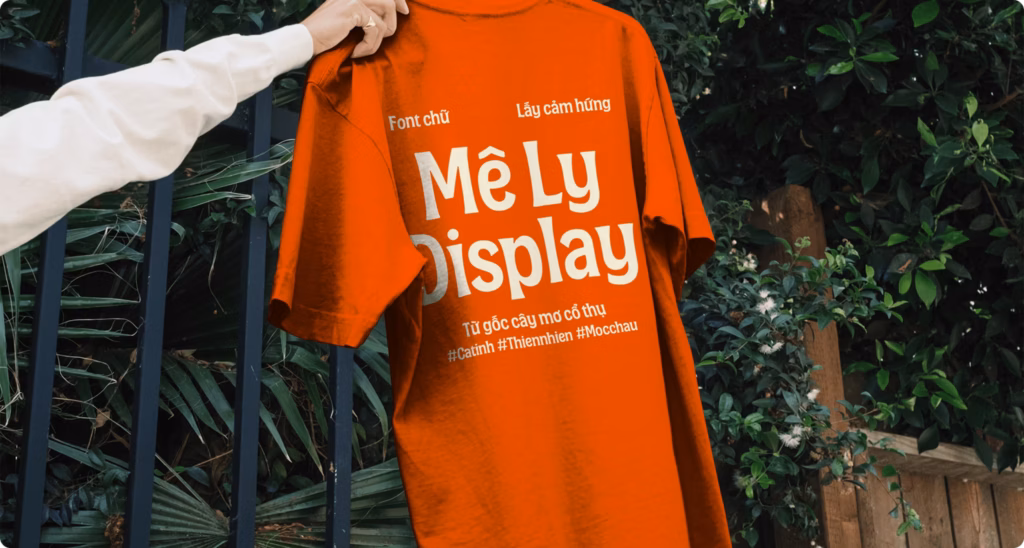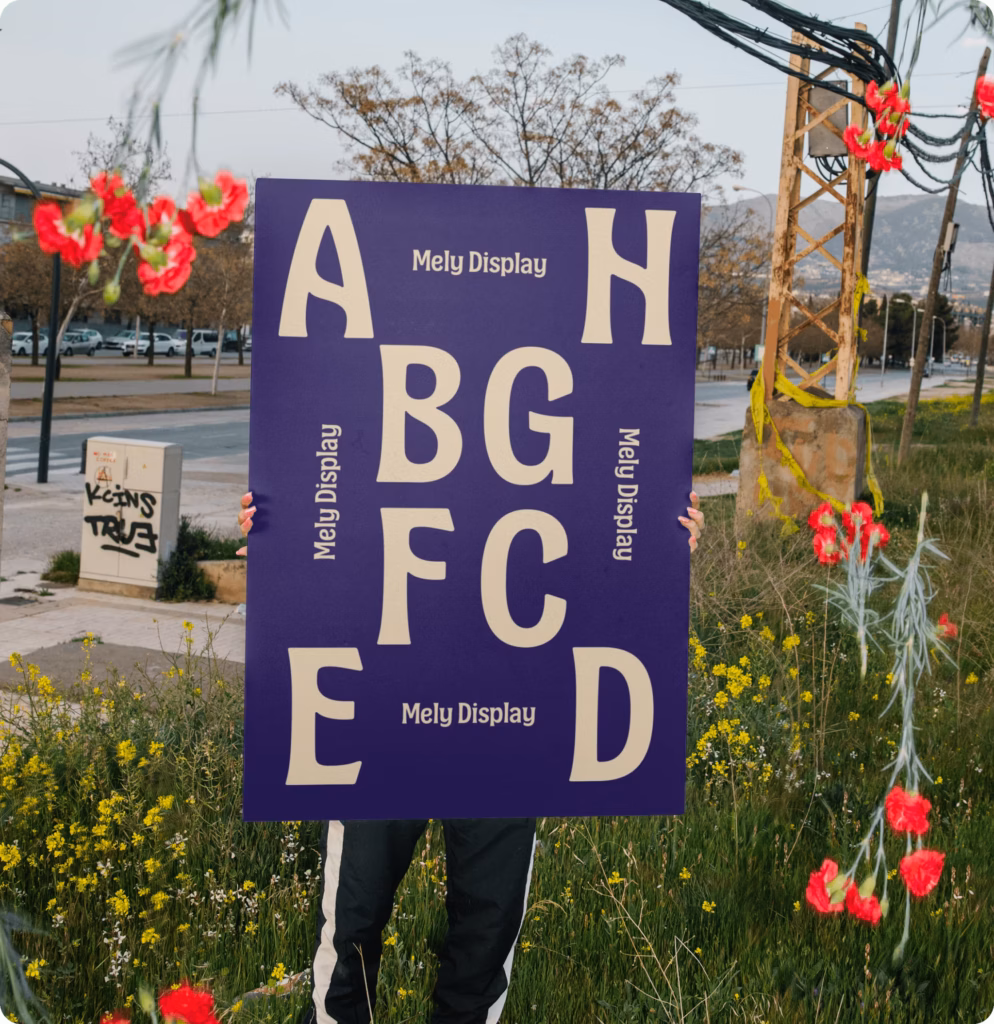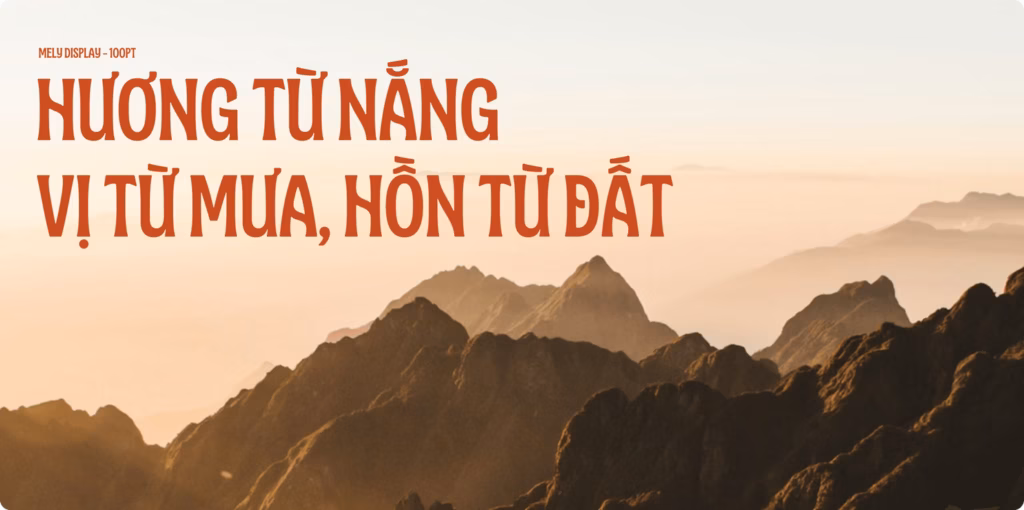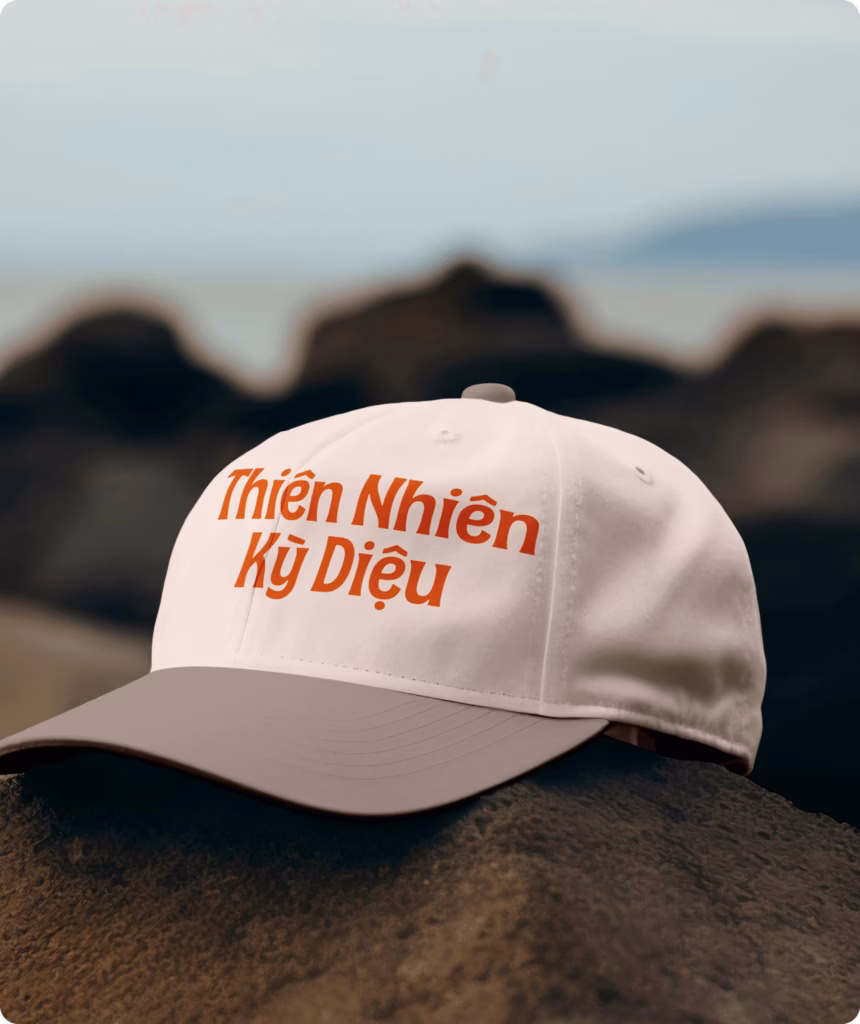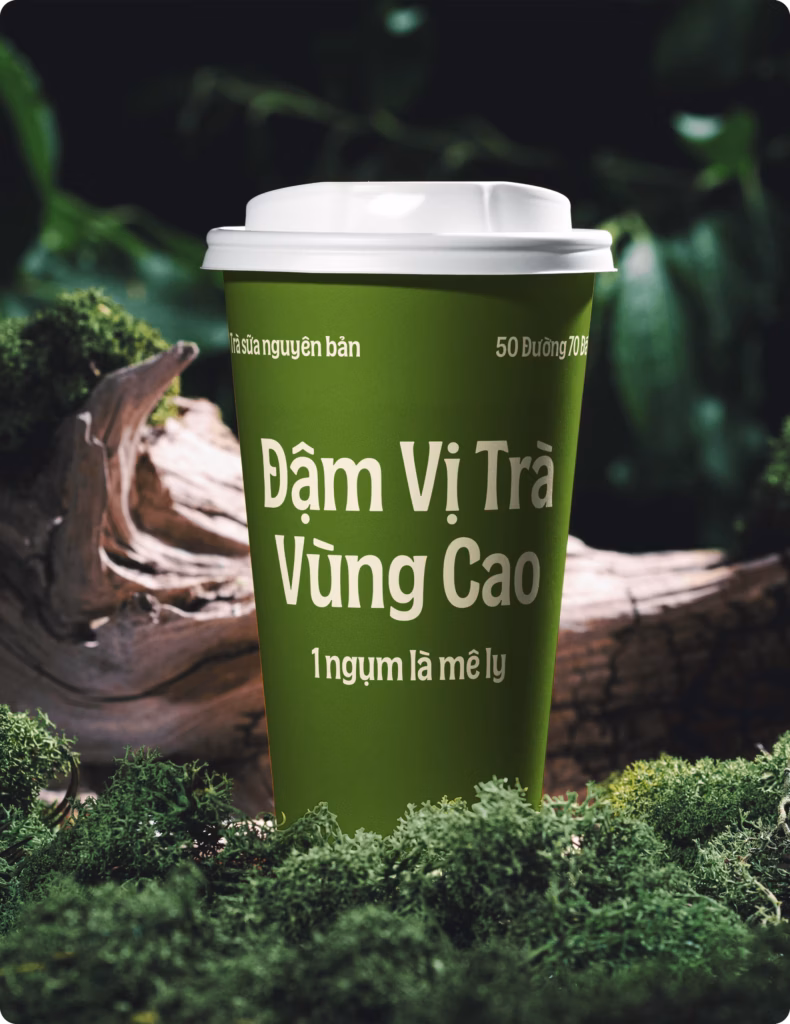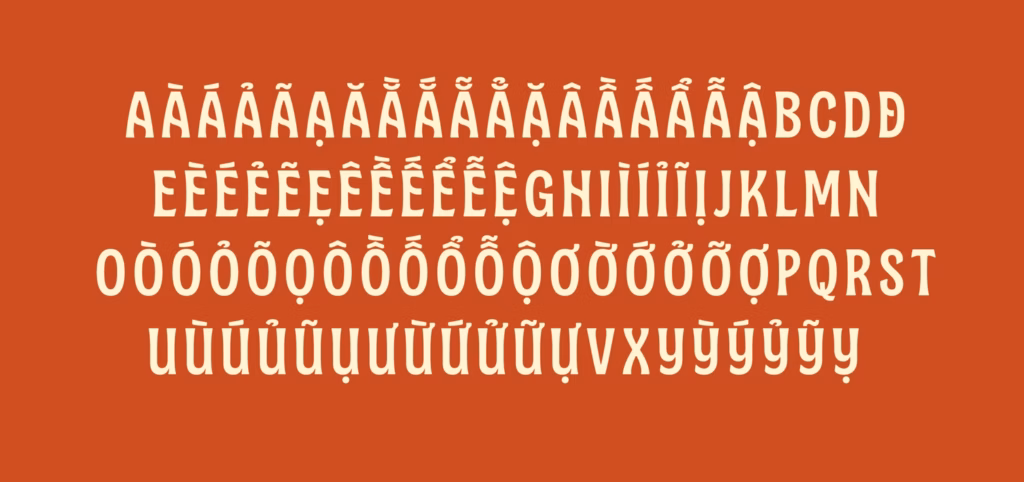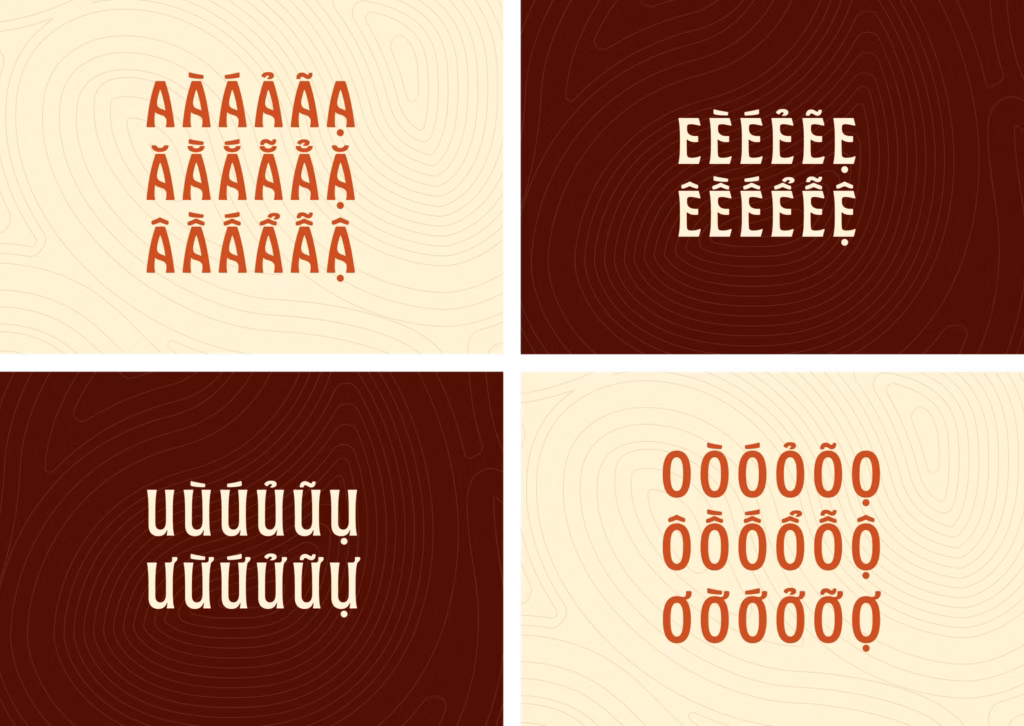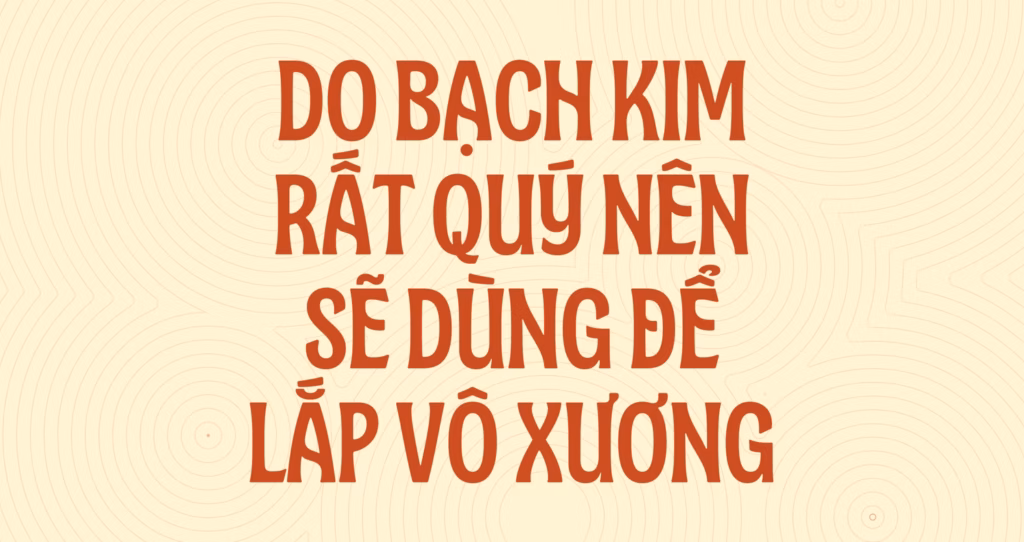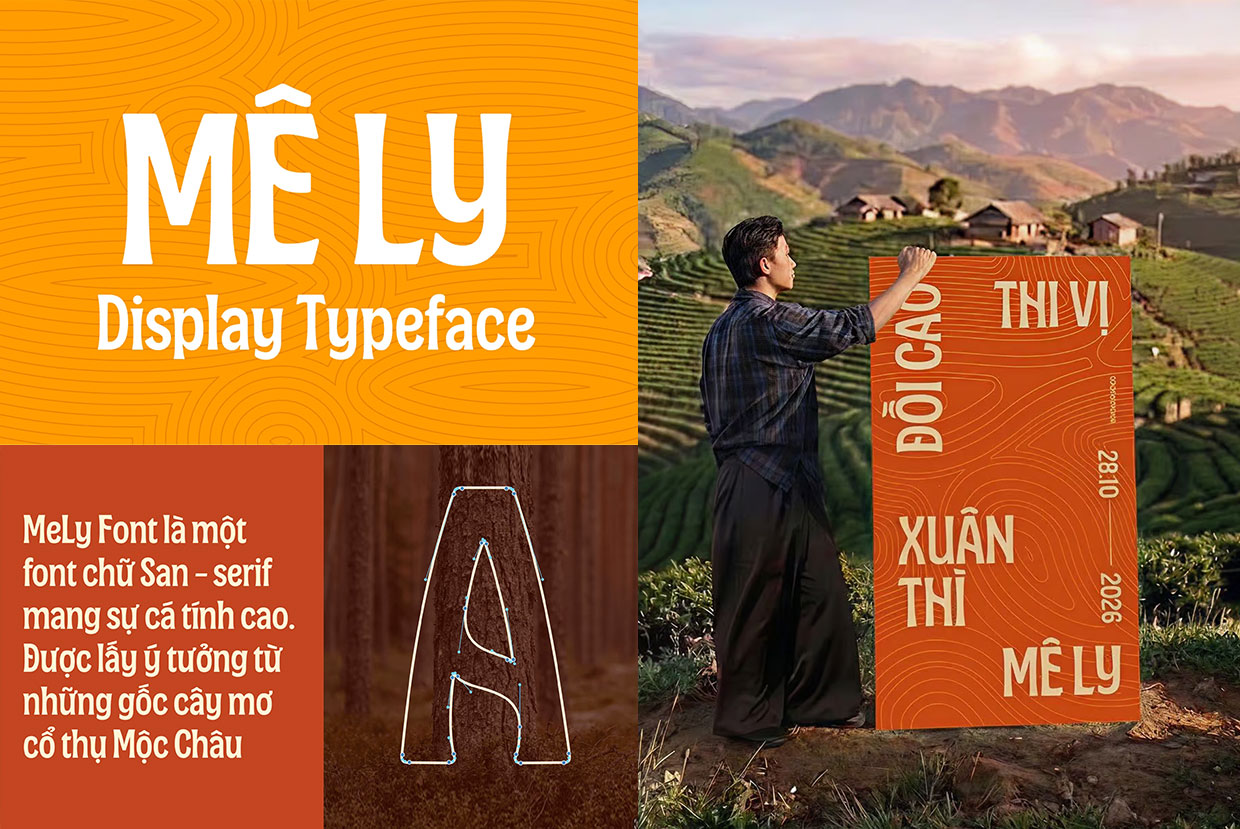
Mê Ly Display là bộ font chữ tiếng Việt được thiết kế bởi Collective Design Agency, lấy cảm hứng từ những vườn mơ cổ thụ (Prunus armeniaca) ở Mộc Châu. Được gió núi, sương giá và thời gian bồi đắp qua nhiều năm, những thân cây mang một vẻ đẹp vừa thô ráp, mạnh mẽ, vừa mềm mại và đầy tinh tế.
Ban đầu bộ typeface được thiết kế dành riêng cho thương hiệu rượu mơ Mơ Ly, Mê Ly Display đã biến tinh thần của vùng đất Mộc Châu thành một “giọng nói thị giác” – có thể vượt ra khỏi bối cảnh ban đầu để tiếp tục hiện diện trong nhiều dự án và không gian sáng tạo khác nhau.
Biến di sản thành một giá trị có thể ứng dụng
Đề bài đặt ra là tạo nên một bộ chữ có thể truyền tải tinh thần của Mơ Ly mà không cần dựa vào những mô-típ văn hóa quen thuộc.
Thay vì xem vườn mơ chỉ như một yếu tố trang trí, nhóm thiết kế nhìn nhận nơi đây như một hệ thống của những sự đối lập: cũ kỹ nhưng đầy sức sống, vững chãi nhưng tinh tế, được thời gian bồi đắp nhưng vẫn hồi sinh vào mỗi độ xuân về. Chính những đặc tính ấy đã trở thành nguồn cảm hứng để tạo nên một bộ chữ display vừa mang đậm bản sắc Việt Nam, vừa phù hợp với ngôn ngữ thiết kế đương đại.
Vững trong cấu trúc, mềm trong nhịp điệu
Mê Ly Display kết hợp những ký tự in hoa mạnh mẽ, dứt khoát với các ký tự thường có đường nét mềm mại hơn. Bộ chữ sở hữu tỷ lệ gọn gàng và giàu tính điêu khắc, được thiết kế để tạo ấn tượng mạnh ngay cả với những từ ngắn khi sử dụng ở kích thước lớn.
Các đường cong tinh tế, chi tiết thuôn nhẹ và sự chuyển tiếp tự nhiên giữa các nét giúp bộ chữ không trở nên cứng nhắc. Tất cả hòa quyện để tạo nên một kiểu chữ đủ nổi bật làm điểm nhấn của bố cục, nhưng vẫn giữ được cảm giác ấm áp và giàu chuyển động.
Bộ font chữ bao gồm đầy đủ chữ in hoa, chữ thường, hệ thống dấu tiếng Việt, chữ số, dấu câu và một số ký tự thay thế được thiết kế riêng.
Nhịp điệu được dệt nên từ chính ngôn ngữ
Khi nguyên âm và phụ âm kết hợp, chúng tạo nên một dòng chảy nhịp nhàng, gợi cảm giác hài hòa nhưng vẫn đầy nội lực. Cấu trúc của mỗi ký tự, với những đường cong nhẹ nhưng vững chãi, gợi liên tưởng đến thân cây và lớp vỏ sần của những cây mơ cổ thụ – bám rễ sâu trong di sản, nhưng vẫn không ngừng vươn cành và tỏa sức sống vượt thời gian.
Được thiết kế cho tiếng Việt ngay từ đầu
Hệ thống dấu tiếng Việt là một phần cốt lõi trong thiết kế của Mê Ly Display, chứ không phải được bổ sung sau khi các ký tự cơ bản đã hoàn thiện.
Mỗi dấu thanh đều được thiết kế và căn chỉnh khoảng cách cẩn thận nhằm đảm bảo sự rõ ràng, cân đối và khả năng biểu đạt trong mọi tổ hợp thanh điệu. Nhờ đó, các từ tiếng Việt vẫn giữ được nhịp điệu và sức biểu đạt thị giác, ngay cả khi được trình bày ở kích thước lớn hoặc trong những bố cục có mật độ chữ dày.
Mê Ly Display của CDA là lời tri ân dành cho những vườn mơ cổ thụ ở Mộc Châu, nơi những thân cây được gió núi và sương giá của vùng cao hun đúc qua hàng chục năm nhưng vẫn bừng nở mỗi độ xuân về. Chính sự đối lập đầy lặng lẽ giữa vẻ đẹp phong trần và sức sống tái sinh ấy đã trở thành nguồn cảm hứng cho bộ chữ này.
CDA là một đơn vị tư vấn sáng tạo ra đời tại Việt Nam với tư duy toàn cầu. Thông qua những bộ chữ như Mê Ly Display, CDA mong muốn đưa một phần cảnh quan, chất liệu và tinh thần thủ công của Việt Nam đến với cộng đồng sáng tạo trên khắp thế giới.